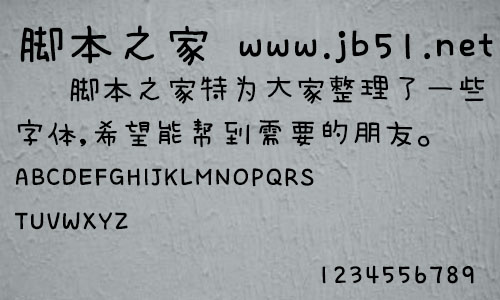
淺淺芒果體是一款藝術(shù)字體,這款字體造型比較隨意,就像芒果一樣胖乎乎的,也像一個(gè)孩子寫(xiě)的字體,歪歪扭扭的,適合應(yīng)用于藝術(shù)設(shè)計(jì)、平面宣傳設(shè)計(jì)、網(wǎng)頁(yè)設(shè)計(jì),書(shū)法字帖等領(lǐng)域。